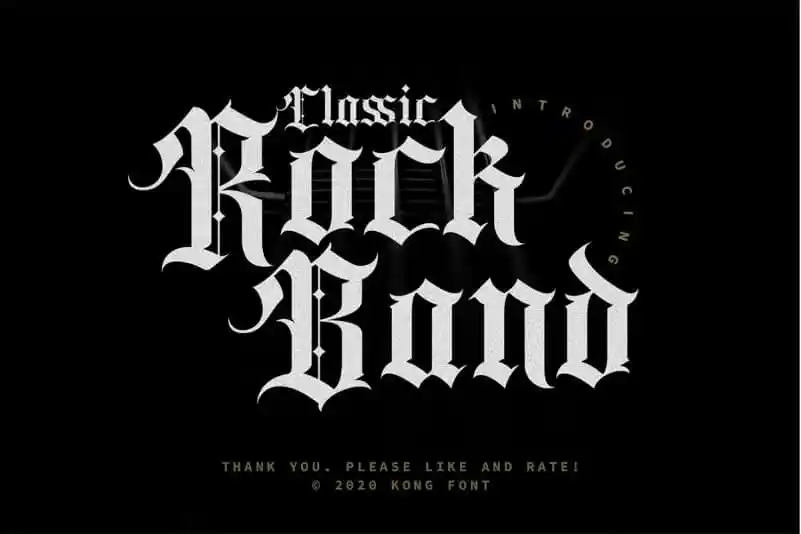
Classic Rock Band Blackletter Font – Download Grátis
Aqui está uma breve e envolvente descrição para a página de download da font ‘Classic Rock Band Blackletter Font’ na categoria dos fonts Redondos: Gostaríamos de apresentar à você um novo tipo de font, a Classic Rock Band Blackletter Font. Esta é uma tipografia inspirada no estilo vintage do blackletter, um estilo tipográfico caracterizado por letras mais largas e sinuosas. A fonte foi criada pelo designer fontkong em 99designs, um lugar onde designers compartilham e desenvolvem novos projetos. O Classic Rock Band Blackletter Font combina elementos do estilo de tatuagem e ornamentos perfeitamente para uso em desenhos de tatuagens, criação de logotipos para salões de tatuagem, design de camisetas, painéis publicitários, marcas de marca ou qualquer projeto que exija um look vintage moderno. Esta font é perfeita para quem busca uma opção original e criativa para projetos gráficos, dando vida aos desenhos digitais com uma dose atraente de personalidade e estilo retro. Não espere apenas por mais um simples tipo de texto em seu próximo projeto — o Classic Rock Band Blackletter Font oferece tanto personalidade quanto sofisticação, combinando elementos vintage e modernos para tornar seu trabalho ainda mais único.